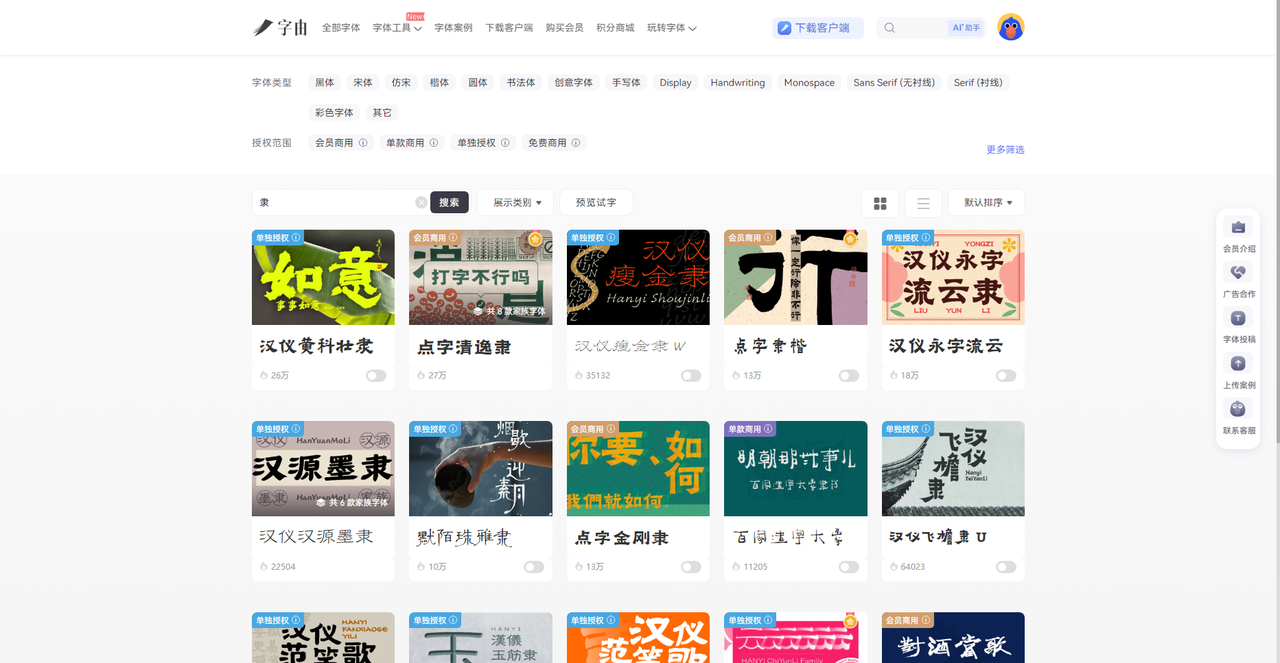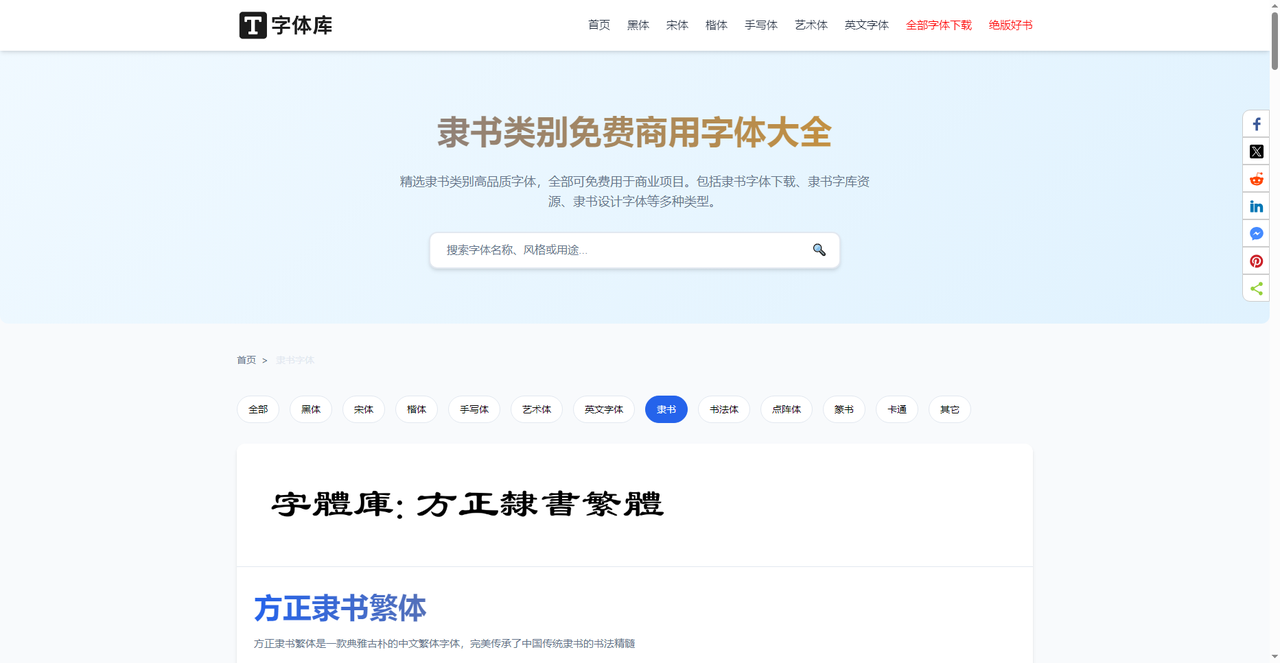
隶书字体转换器怎么用?输入文字一键生成古朴隶书
隶书是中国书法中极具辨识度的字体,字形扁方、横长竖短,笔画讲究“蚕头雁尾”,给人一种端庄古朴、稳重典雅的感觉。做中式餐厅招牌、茶叶包装、国潮海报、文化展馆导视,隶书总能让氛围感瞬间拉满。但是系统自带的中文字体里隶书选项极少,不过现在有了在线隶书字体转换器,你只需要输入汉字,选择喜欢的隶书风格,就能生成高清隶书艺术字图片,或者直接下载隶书字体安装到电脑里使用。今天实测了5款隶书字体转换工具,从字由的AI字效和专业隶书库到在线参数调节站,覆盖了设计师和个人用户的不同需求。
方法一:AI字体生成隶书
打开字由客户端,进入“AI工具”下的“AI字体”。在模板库里搜索关键词“隶书”“古朴”“国潮”“书法”,或者直接浏览“国潮风”“手写书法”等分类。你会发现不少带有隶书笔意的模板——这些模板不只是简单地把文字变成隶书形状,还配好了仿古宣纸纹理、石碑拓印质感、墨迹晕染效果。比如截图中的“汉仪黄科壮隶”,笔画雄强有力,蚕头雁尾明显,特别适合做牌匾大字。
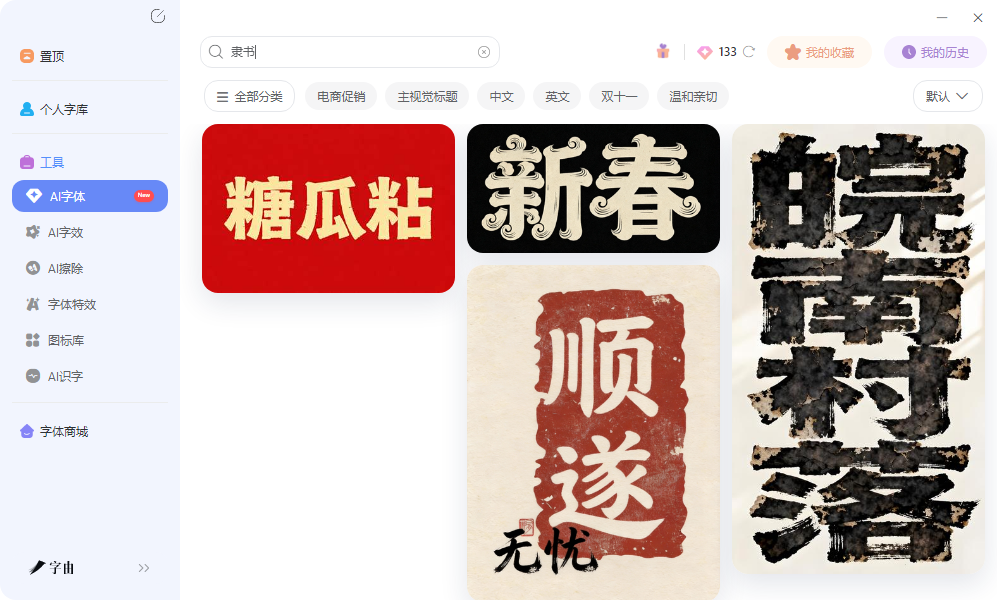
方法二:激活隶书字体
- 汉仪黄科壮隶(单独授权,笔画雄强,适合大字招牌)
- 汉仪瘦金隶W(融合瘦金体与隶书特点,瘦劲飘逸)
- 点字清逸隶(清秀淡雅,适合文艺类包装)
- 点字隶楷(隶书与楷书结合,结构规整)
- 汉仪永字流云(笔画流畅,云纹装饰感)
2、T字体库
第二个网站是T字体库(截图中的第二张图)。它专门整理了隶书类别的免费商用字体。首页就有“隶书类别免费商用字体大全”板块,声明“精选隶书类别高品质字体,全部可免费用于商业项目。包括隶书字体下载、隶书字库资源、隶书设计字体等多种类型。”在分类导航里可以快速筛选,这个站的优点在于所有字体都明确标注免费可商用,省去了设计师自己查版权的麻烦。下载方式简单直接,点击字体即可跳转到下载页面。适合需要快速找到高质量免费隶书字体的用户。
3、篆书体网站
第三个网站是一个综合性的书法字体转换平台。它的核心功能是“请在下面输入文字后点击生成篆体字”,但同样支持隶书字体。页面提供了多种隶书字体选项,如“方正小繁体”“汉仪粗篆繁”“汉仪篆书繁”“方正悬针篆变”等,这些虽然是篆书为主,但部分带有隶书元素。不过为了用户明确需求,我们可重点看它的转换逻辑。
4、字体视界
第四个网站是字体视界旗下的“隶书字体转换器”。页面提供了完整的转换工具:在输入框输入文字,从下拉菜单中选择字体(例如“汉呈施申财隶书字”),然后可以对文字效果进行多种调节——更多色彩、横向渐变、阴影、线性渐变、投影、空心字、径向渐变、转音、磨砂金等。还可以批量下载,调整高度宽度(默认1200x300),设置背景颜色或透明底,字体大小(默认100)。设置好后点击生成,即可得到高清隶书图片。
5、免费字体网
第五个网站是免费字体网。它提供了一个“隶书字体在线预览”工具,用户可以在输入框输入文字,设置字体大小(40px)、字体颜色、背景颜色,勾选“使用透明背景”和“转为繁体字”,然后点击“立即转换”,即可生成隶书效果预览图片。页面下方还有字体在线转换器的说明和热门字体推荐。另外,页面右侧还有免费商用字体推荐、VIP服务、海报制作工具等,但核心功能就是隶书在线预览转换。对于只需要快速试一下隶书效果、不做深层次设计的用户来说,这个工具足够用了。
五个隶书字体转换工具,各有侧重。字由最适合专业设计师,AI字体直接生成古朴隶书特效图,会员商用隶书字体库激活后在PS里反复使用,适合品牌VI和长期项目;T字体库精选免费商用隶书,所有字体标注可商用,下载省心;篆书体网站支持隶书转换并可调节多种参数,适合自己动手调效果;字体视界提供特效丰富的隶书转换器,还能购买正版授权;免费字体网最轻量,快速预览和转换,适合个人学习参考。输入想要转换的文字,选择喜欢的隶书风格,不论做什么样的所设计,这里总有一款工具能帮助你找到喜欢的那款字体。